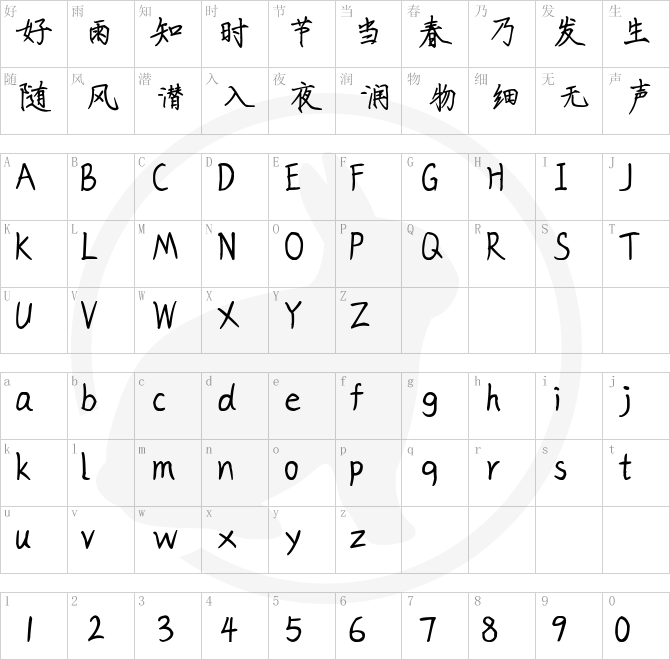
YEFONTQinqLangShouJinTi 標準
YEFONTQinqLangShouJinTi 標準,这款字体结构工整、笔画清晰,兼顾美观与易读性,适用于标题、正文、海报、包装、LOGO 等多种场景。字形优雅稳定,风格百搭耐看,适配日常排版与创意设计,让文字呈现更舒适、更具质感。YEFONTQinqLangShouJinTi 標準一笔一画,皆是细节,以均衡的比例、流畅的线条打造舒适视觉体验,字形端正大气,风格简约现代。无论是商业设计、品牌宣传还是日常排版,都能轻松驾驭,让文字更有格调与力量。YEFONTQinqLangShouJinTi 標準字体下载。